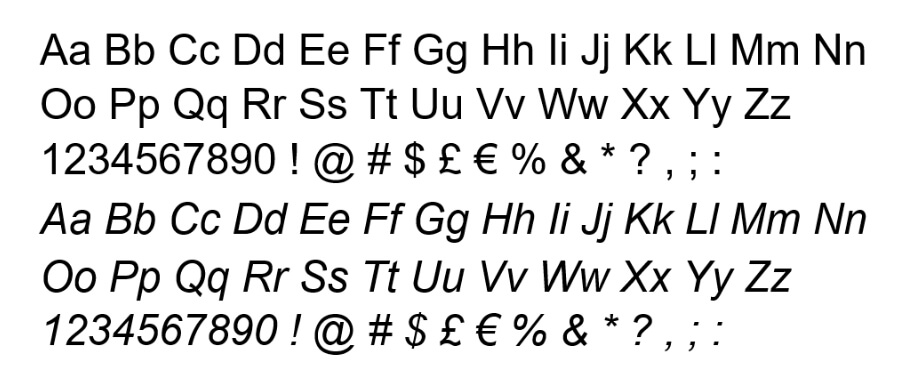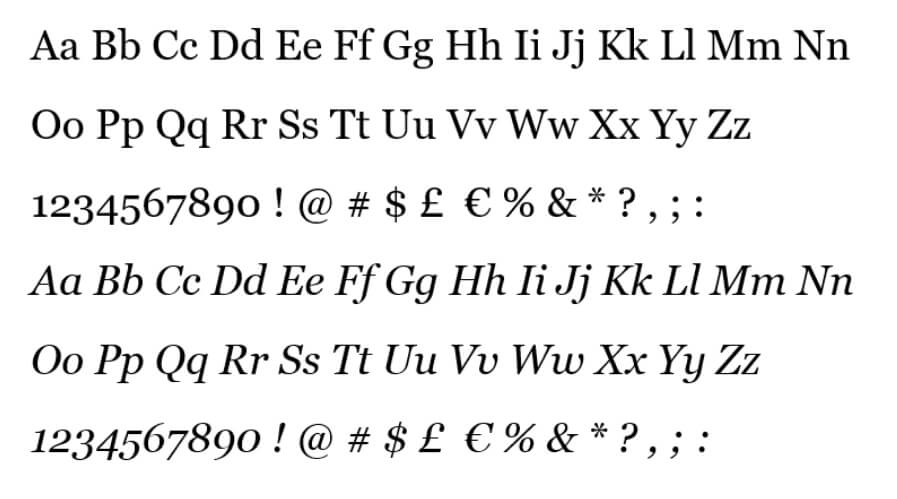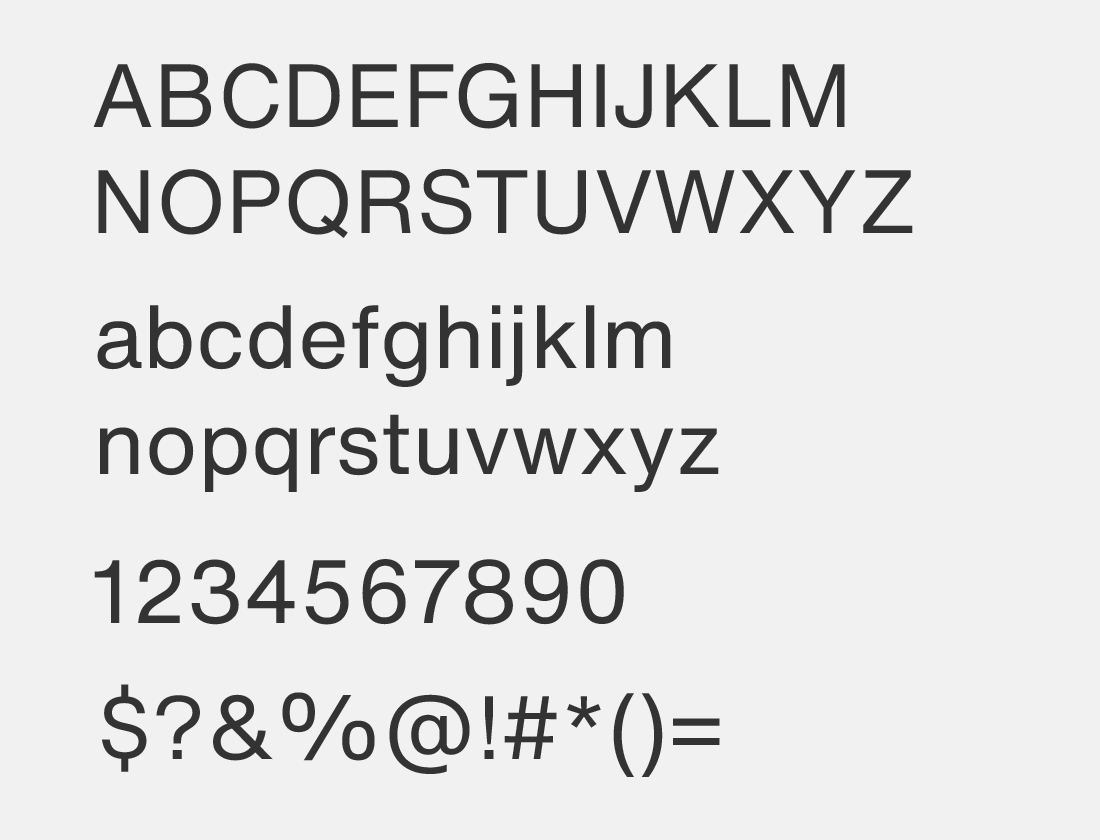
Чтобы письма дочитывали до конца
Читатель тратит на письмо до 15 секунд. Смотрит тему, картинки, захватывает заголовки. Под интересными заголовками читает текст. Выбор — перейти по ссылке из письма или нет — делается молниеносно. Во многом это зависит от шрифта — он определяет, насколько легко читать письмо.
Задача шрифта — быть приятным глазу и упрощать чтение. Текст, который легко читать, дочитывают до конца. Это заслуга не только автора, но и типографики. Рассказываем, как выбрать шрифт, чтобы подписчикам было удобно читать письма.
Сравним популярные шрифты в рассылках.
Шрифт №1 в Европе и США. Создан в Швейцарии в 1957 году. Простой, изящный, нейтральный и универсальный. Без засечек. Helvetica — самый популярный шрифт в айдентике мировых брендов. Toyota и Skype, McDonalds и Nestle выбрали его для общения с потребителями.
Преимущества Helvetica — простота и гармоничность. Шрифт идеален, если хотите понравиться всем.
Популярнейший компьютерный шрифт. Создан в 1982 году на основе Helvetica. Преимущества те же: простота, нейтральность, универсальность.
Оба выставлены по умолчанию в популярных почтовых сервисах: например, Apple Mail использует Helvetica, Gmail — Arial (если браузер не поддерживает Arial, происходит автоматическое переключение на Helvetica).
Кириллицу Arial и Helvetica создали англоговорящие шрифтовики, и они учли не все особенности языка. Некоторые буквы выглядят идентично (п-л, ы-ь, ц-и, ч-н).
Не рекомендуем Arial и Helvetica в длинных текстовых письмах. Будет выглядеть стильно, но однообразно.
Знаменитый шрифт с засечками — короткими штрихами на конце буквы. Раньше считали, что засечки усложняют чтение. Но типограф Джерри Леонидас утверждает, что засечки улучшают восприятие и способствуют прочтению текста до конца:
Verdana не имеет засечек. Характерная особенность этого шрифта — широкий внутрибуквенный просвет. Буквы имеют открытую форму, это приятно для чтения.
Текст, набранный Verdana, читается легко. Поэтому его часто используют в email-рассылках.
Разработан в 1932 году специально для лондонской газеты The Times. Популярен в России, особенно в официальных документах, коммуникациях государственных органов и вузов.
Почти все договоры на русском набраны в Times New Roman. Быть может, из-за официозности маркетологи используют шрифт менее активно.
Почтовые клиенты воспринимают не все шрифты для email рассылки. Вот список из самых «безопасных». Их отобразит любой почтовый клиент.
Без засечек:
Рукописные:
С засечками:
Моноширинные:
Многие популярные почтовики постепенно добавляют поддержку веб-шрифтов. Например, Gmail и Apple Mail. Outlook на Mac. Если письмо с веб-шрифтом придет человеку, почтовик которого такие шрифты не поддерживает — текст письма отобразиться в Times New Roman для шрифтов с засечками и Arial для шрифтов без засечек. При этом верстка может съехать.
Вы можете использовать для своих писем небезопасные веб-шрифты. Но в этом случае нужно подстраховываться и прописать, какой шрифт использовать почтовику, если у него будут проблем с отображением. Этот второй шрифт должен быть безопасным, из списка выше.
Указать резервный шрифт можно таким кодом:
Десктоп-версии Outlook будут переводить некоторые шрифты в Times New Roman. С этим можно бороться, если вы немного разбираетесь в верстке. Добавляем в email этот код:
А затем используем класс "fallback-text", когда нужно избавиться от стандартного Times New Roman.
Айдентика (фирменный стиль) бренда едина во всех каналах коммуникации. Это аксиома. Поэтому все значимые элементы дизайна, в том числе и шрифты, прописываются в брендбуке.
Если брендбука нет — запомните 4 простых правила:
1. Разные шрифты для заголовка и абзаца. Конкретных указаний нет — все зависит от вашей фантазии, корпоративного стиля и возможностей почтовой программы. Моё мнение: чередовать шрифты с засечками и без — красиво.
2. Минимум декоративных шрифтов. Они плохо читаются в больших письмах и не всегда правильно отображаются в почте. Зато изысканный редкий шрифт можно безбоязненно использовать в фото и иллюстрациях.
3. Соблюдайте стилистику письма. Шрифт дополняет содержание текста: странно видеть аналитический отчет о проделанной работе компании в рукописном шрифте. Для официальных писем и серьезных рассылок, подойдут сдержанные и нейтральные шрифты. Для шуточных писем или развлекательного контента можно использовать более неформальные.
4. Выберите 2-3 основных шрифта. И используйте постоянно. Они — ваша визитка. Пусть читатель привыкнет к вашему стилю. Двух-трёх шрифтов вполне хватит для узнаваемости.
С ним аккуратно. Подчёркивание прочно ассоциируется со ссылкой. Нет ссылки — лучше не подчёркивать.
У каждого шрифта своя высота и ширина букв, поэтому универсальных требований по размеру назвать не получится. Но есть примерные параметры, которых стоит придерживаться:
Текст размером 10 px и меньше сложно читать, поэтому его лучше использовать для сносок, уточнений или футера.
Цвет может как улучшить, так и испортить впечатление от письма. Выбирайте аккуратно: